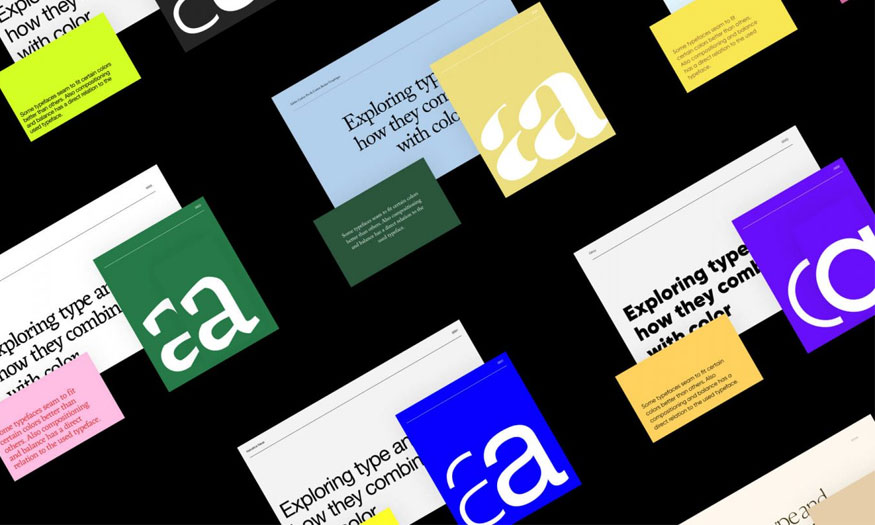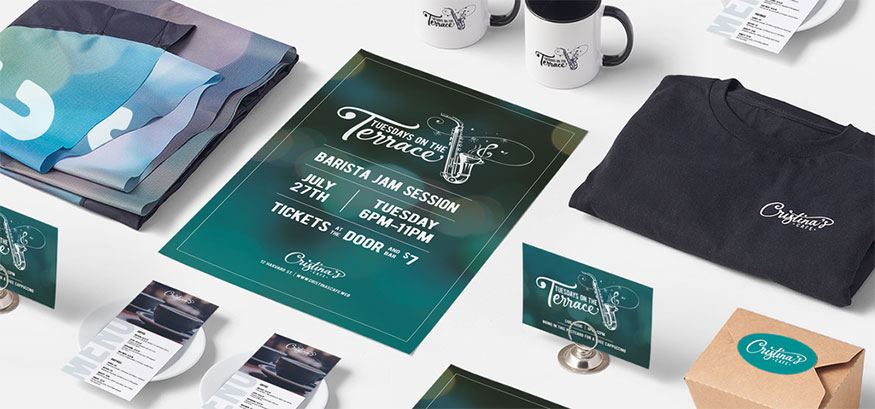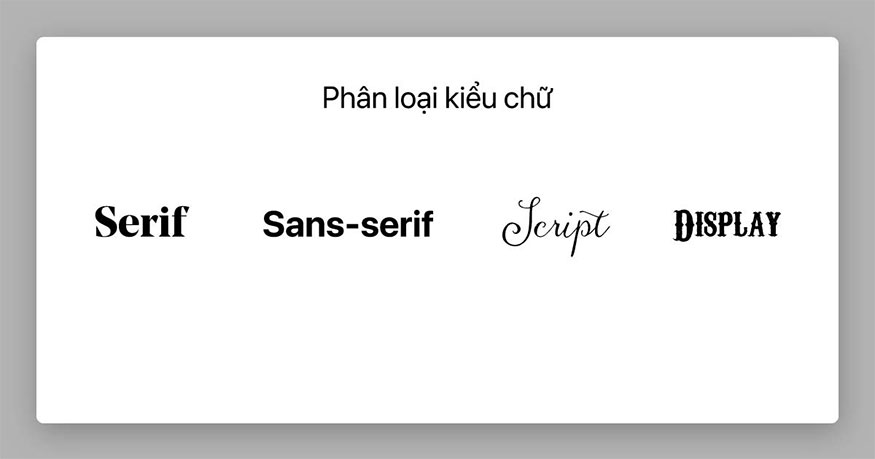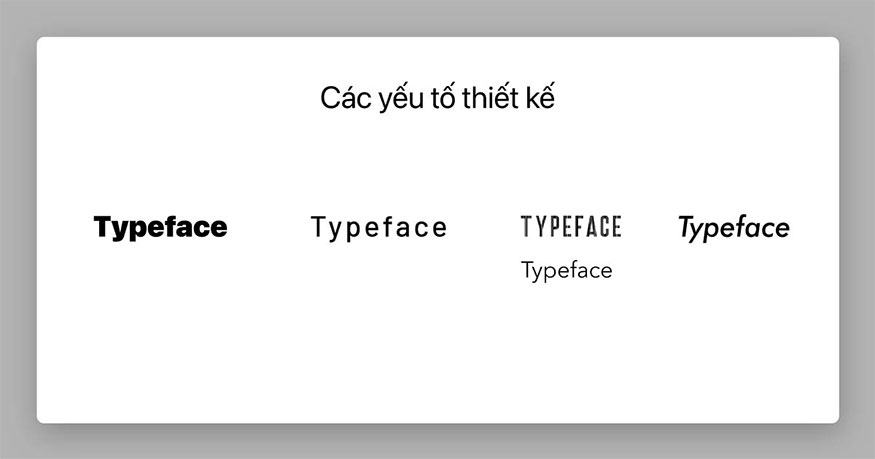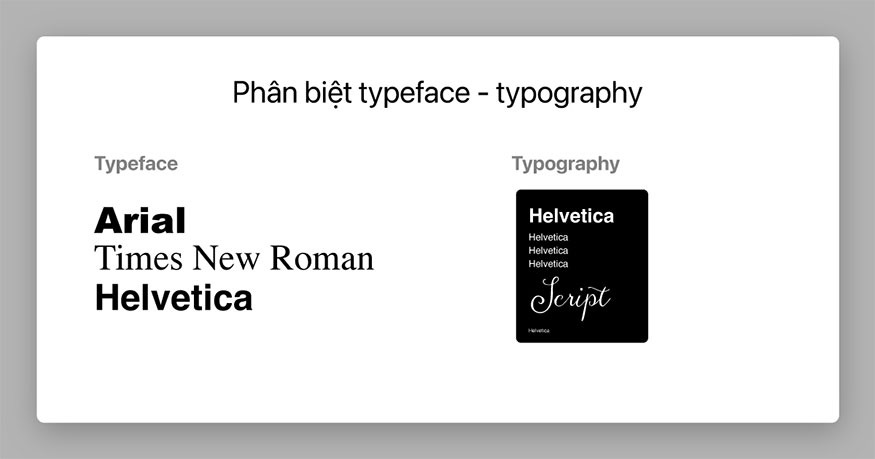
Brand Typeface là gì? Phân biệt Font, Typeface và Typography
Brand typeface là kiểu chữ thương hiệu được sử dụng phổ biến hiện nay với khả năng truyền tải thông điệp hiệu quả. Tuy nhiên hiện có khá nhiều bạn vẫn chưa hiểu rõ về khái niệm này.
Brand typeface là kiểu chữ thương hiệu được sử dụng phổ biến hiện nay với khả năng truyền tải thông điệp hiệu quả. Tuy nhiên hiện có khá nhiều bạn vẫn chưa hiểu rõ về khái niệm này. Vậy trong bài viết này, SaDesign sẽ giúp bạn đọc hiểu rõ hơn về khái niệm brand typeface, cũng như phân biệt sự khác nhau cơ bản giữa font, typeface, và typography.
1. Brand typeface là gì?
Brand typeface hay còn được gọi là kiểu chữ thương hiệu, chúng có thể là một phông chữ hoặc một bộ phông chữ có khả năng nhận diện thương hiệu mạnh mẽ.
Có thể thấy Brand typeface là yếu tố quan trọng trong bộ nhận diện thương hiệu để truyền tải thông điệp, xây dựng hình ảnh nhất quán. Ví dụ điển hình như thương hiệu đình đám trên thị trường hiện nay như Coca-Cola hay Google, có thể thấy các “ông lớn” thì thiết kế kiểu chữ được xem là một phần không thể tách rời nhằm thể hiện giá trị và bản sắc thương hiệu.
Việc lựa chọn brand typeface phù hợp đặc biệt quan trọng, chúng có ảnh hưởng trực tiếp đến sự thành công của thương hiệu cũng như quyết định của người mua hàng đối với sản phẩm mà bạn cung cấp.
2. Brand typeface trong tâm lý học
Nhiều nghiên cứu trong tâm lý học đã chỉ ra rằng yếu tố trực giác và cảm xúc có tác động mạnh mẽ quyết định mua hàng của người dùng. Vì thế cho nên brand typeface có vai trò then chốt với khả năng khơi gợi cảm xúc tích cực, thúc đẩy hành vi mua hàng.
Nghiên cứu tâm lý học về brand typeface mặc dù mới xuất hiện nhưng hiện đang nhận được sự quan tâm mạnh mẽ trong giới thiết kế đồ họa và phát triển thương hiệu. Theo đó người ta tập trung vào việc tìm hiểu cách phông chữ ảnh hưởng đến cảm xúc, nhận thức, hành vi của người dùng với thương hiệu.
Nghiên cứu tâm lý học về brand typeface tập trung vào những yếu tố sau:
2.1. Kiểu Chữ
Kiểu Chữ
Về kiểu chữ trong tâm lý học được phân loại với các kiểu như sau, mỗi kiểu sẽ đại diện cho những cảm giác về thị giác khác nhau:
• Serif: Đây là dạng kiểu chữ có chân, thiết kế của kiểu chữ này giúp khơi gợi lên cảm giác sang trọng, cổ điển, đáng tin cậy. Vì thế chúng thường phù hợp cho những thương hiệu lâu đời hay doanh nghiệp kinh doanh mặt hàng cao cấp.
• Sans-serif: Đây là kiểu chữ không chân với hiệu ứng tối giản, hiện đại và trẻ trung. Kiểu chữ này rất thích hợp với những thương hiệu công nghệ, sản phẩm cho giới trẻ,...
• Script: Đây là kiểu chữ viết tay vô cùng sáng tạo, thanh lịch, vì thế cho nên kiểu chữ này được dùng phổ biến trong các thương hiệu thời trang, mỹ phẩm, sản phẩm chứa yếu tố nghệ thuật.
• Display: Đây là kiểu chữ trang trí được thiết kế độc đáo, bắt mắt. Kiểu chữ này thường được được dùng để tạo điểm nhấn với khả năng tạo sức hút cao. Theo đó, kiểu chữ này được xem là lựa chọn hàng đầu của những thương hiệu giải trí, sự kiện,...
2.2. Các yếu tố ảnh hưởng trong thiết kế brand typeface
Các yếu tố ảnh hưởng trong thiết kế brand typeface
Sau đây là những yếu tố quan trọng ảnh hưởng đến lĩnh vực thiết kế brand typeface mà bạn nên biết và hiểu rõ:
• Độ dày của nét chữ: Những nét chữ dày có tác dụng mang đến cảm giác mạnh mẽ, tự tin, tràn đầy nam tính, còn những nét chữ mỏng tạo cảm giác tinh tế, nhẹ nhàng và tràn đầy nữ tính.
• Khoảng cách các chữ cái: Các chữ cái có khoảng cách hẹp thường tạo cảm giác gần gũi, còn khoảng cách rộng sẽ tạo nên cảm giác hiện đại và sang trọng.
• Chiều cao chữ: Với những chữ cao tạo mang đến cảm giác trang trọng, cổ điển, còn chữ thấp tạo cảm giác gần gũi nhưng không kém phần hiện đại.
• Độ nghiêng chữ: Với chữ nghiêng sẽ mang đến sự năng động, sáng tạo cho kiểu chữ, còn với chữ thẳng tạo cảm giác nghiêm túc xen lẫn nét truyền thống.
3. Phân biệt giữa font, typeface và typography
3.1. So sánh nhanh
Những so sánh nhanh sau đây sẽ giúp bạn phân biệt được sự khác nhau cơ bản giữa font, typeface và typography:
Đặc điểm
Font
Typeface
Typography
Định nghĩa
Là tập tập tin kỹ thuật số, tập tin này có chứa các ký tự của một kiểu chữ cụ thể với kích thước và độ đậm nhạt nhất định.
Là bộ sưu tập các font sở hữu chung thiết kế, phong cách và giá trị thẩm mỹ.
Là dạng nghệ thuật sắp xếp, trình bày chữ cái để có được một giao diện trực quan, cuốn hút.
Tính chất
Cụ thể, hữu hình.
Trừu tượng, không phụ thuộc vào kích thước hay định dạng.
Là quá trình sáng tạo, ứng dụng typeface vào trong thực tế.
Vai trò
Được đại diện cho biến thể cụ thể đối với một kiểu chữ.
Gồm những biến thể của một kiểu chữ.
Dùng typeface để tạo được những sản phẩm chữ thẩm mỹ.
Ví dụ
Arial Italic 14pt, Times New Roman Bold 12pt,...
Times New Roman, Arial, Helvetica
Chọn typeface, màu sắc, kích thước, khoảng cách,... để thiết kế các tấm poster, trang web,...
Mối quan hệ
Là một phần của typeface.
Gồm nhiều font khác nhau.
Typeface được dùng để làm nguyên liệu thực hiện.
3.2. So sánh chi tiết
3.2.1. Phân biệt font và brand typeface
Phân biệt font và brand typeface
Font và brand typeface là những khái niệm rất dễ bị nhầm lẫn trong thiết kế. Mặc dù cả 2 đều được dùng để chỉ kiểu chữ, tuy nhiên giữa font và brand typeface có nhiều điểm khác nhau cụ thể như:
Typeface (Kiểu chữ):
• Typeface là tập hợp các ký tự có chung về thiết kế, đặc điểm và phong cách.
• Typeface gồm tất cả các biến thể của một kiểu chữ, bao gồm độ đậm nhạt, độ nghiêng cùng nhiều biến thể khác.
• Ví dụ: Arial, Times New Roman hay Helvetica.
Font (Phông chữ):
• Font được dùng để chỉ một tập tin kỹ thuật số chứa các ký tự của một kiểu chữ với kích thước và độ đậm nhạt nhất định.
• Font chính là một phần của typeface, thể hiện cho một biến thể nào đó của kiểu chữ.
• Ví dụ: Times New Roman Bold 12pt, Arial Italic 14pt.
Nói một cách dễ hiểu thì typeface là một đại gia đình lớn, còn font là những thành viên trong 1 gia đình đó. Mỗi font sở hữu các đặc điểm riêng biệt với độ đậm nhạt khác nhau nhưng đều chung một phong cách thiết kế.
3.2.2. Phân biệt giữa brand typeface và typography
Phân biệt giữa brand typeface và typography
Brand typeface và typography cũng khiến nhiều người bị nhầm lẫn với 2 khái niệm này. Những điểm khác biệt cơ bản mà chúng tôi chỉ ra sau đây sẽ giúp bạn dễ dàng phân biệt được brand typeface và typography:
Typeface (Kiểu chữ):
• Typeface là bộ sưu tập với các ký tự có chung thiết kế, phong cách.
• Typeface bao gồm những biến thể của một kiểu chữ như độ đậm nhạt, độ nghiêng và các biến thể khác.
• Ví dụ: Arial, Times New Roman hay Helvetica.
Typography (Nghệ thuật chữ):
• Typography là kỹ thuật sắp xếp và trình bày chữ cái, điều này nhằm mục đích để tạo nên được một giao diện trực quan và hấp dẫn.
• Typography liên quan tới việc lựa chọn typeface, font, kích thước, khoảng cách,... giữa các chữ cái nhằm mục đích tạo nên được bố cục chữ dễ đọc, thẩm mỹ với khả năng truyền tải thông điệp hiệu quả.
• Typography hiện được sử dụng rất nhiều trong thiết kế đồ họa, in ấn, quảng cáo,...
• Ví dụ: Để thiết kế một poster quảng cáo bạn chọn typeface là Helvetica với font Helvetica Bold 18pt dành cho tiêu đề và nội dung là Helvetica Regular 12pt. Việc lựa chọn kiểu font, typeface, màu sắc hay kích thước,... nhằm để tạo nên bố cục poster hấp dẫn.
Có thể thấy brand typeface là yếu tố quan trọng trong chiến lược xây dựng thương hiệu. Nhờ sự tỉ mỉ trong chi tiết của kiểu chữ giúp khơi gợi cảm xúc của người xem, từ đó để thương hiệu tạo dựng dấu ấn riêng, gây ấn tượng với khách.
Hy vọng với những chia sẻ mà SaDesign mang đến trên đây sẽ giúp doanh nghiệp của bạn lựa chọn và sử dụng kiểu chữ thông minh và ấn tượng để mang đến sự thành công cho chiến dịch marketing của mình.